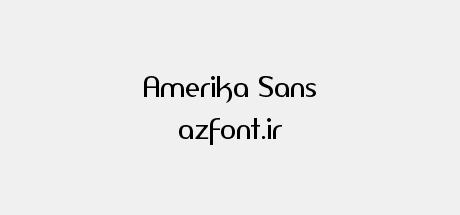
Amerika Sans
فونت زیبای رایگان Amerika Sans
قلم زیبای Amerika Sans از سری قلم های بسیار زیبا برای تایپوگرافی و لوگو تایپ می باشد.این قلم در وزن Regular و توسط AlreoyaNetLight طراحی و منتشر شده است.